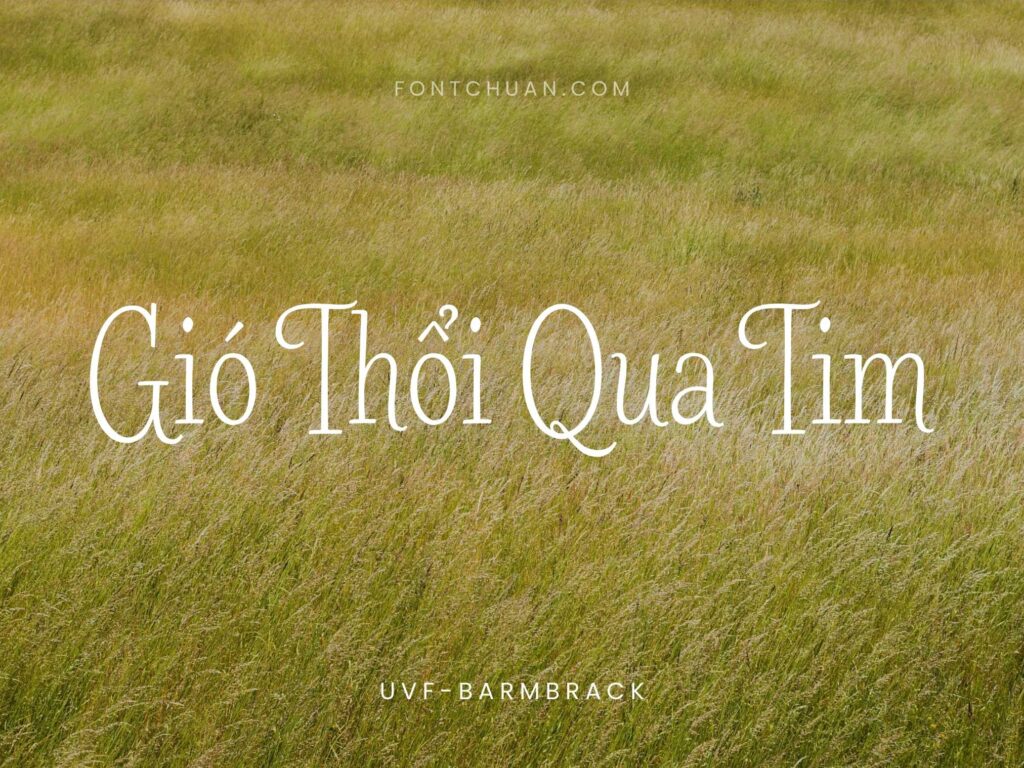
UVF Barmbrack là một phông chữ serif độc đáo, mang phong cách cổ điển với các đường nét tinh tế và sáng tạo. Phông chữ này tạo cảm giác trang nhã và lịch lãm, phù hợp cho các thiết kế như tiêu đề, logo, bao bì sản phẩm và các ấn phẩm in ấn khác. UVF Barmbrack đã được sưu tầm và đăng bởi thành viên của Font Chuẩn.